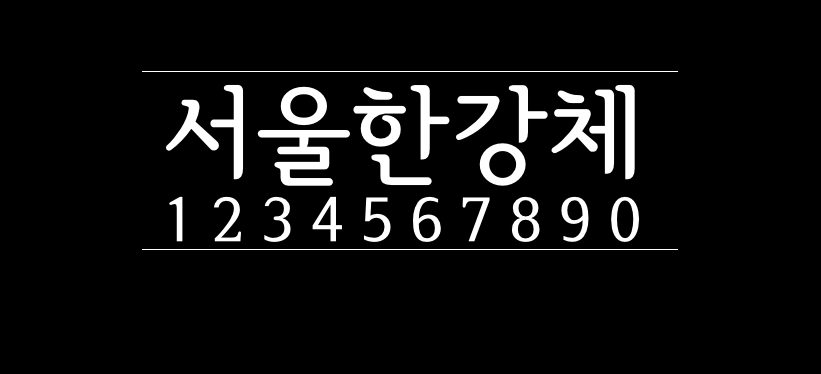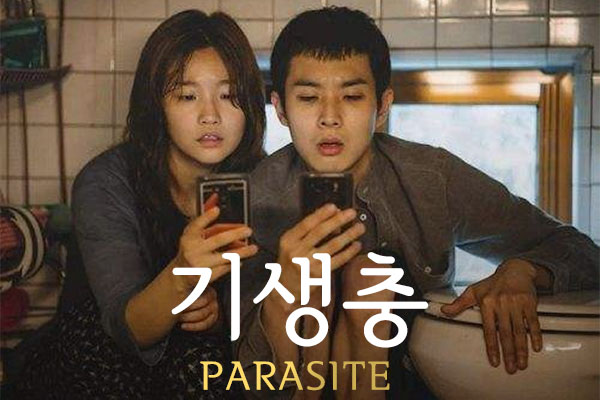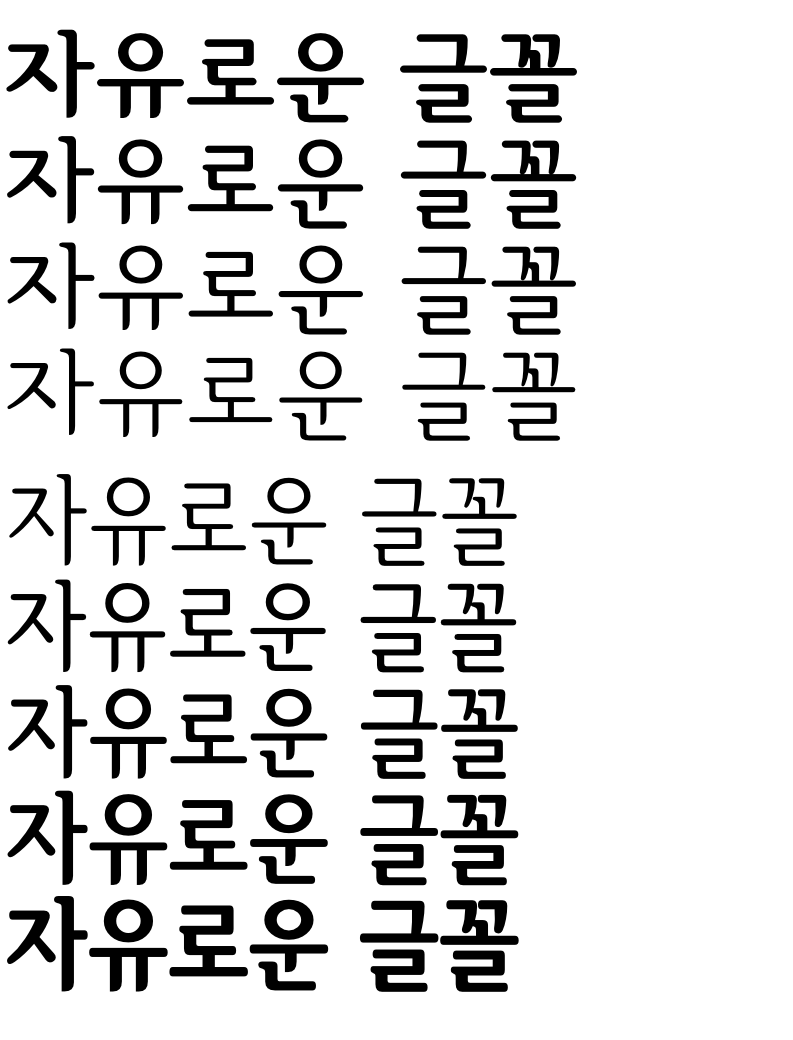
首尔汉江体
首尔汉江体(서울한강체、SeoulHangang)是由韩国首尔政府推出的,在首尔市为广泛使用的韩文字体,提升城市认同性与品牌价值而开发出首尔南山体。
首尔汉江体的特点:减少突起的长度,表现现代式简洁感;为提高可读性而减少装饰性表现;为保持字体固有性而对开头进行了视觉化;通过横向、竖向粗细的均衡感提高字体的鲜明度;简洁的母音结合;删除突起,创造宽敞空间;简洁的子音结合。
首尔汉江体包含长体5种(Light、Medium、Bold、Extra Bold、black)和正体4种(Light、Medium、Bold、Extra Bold)。